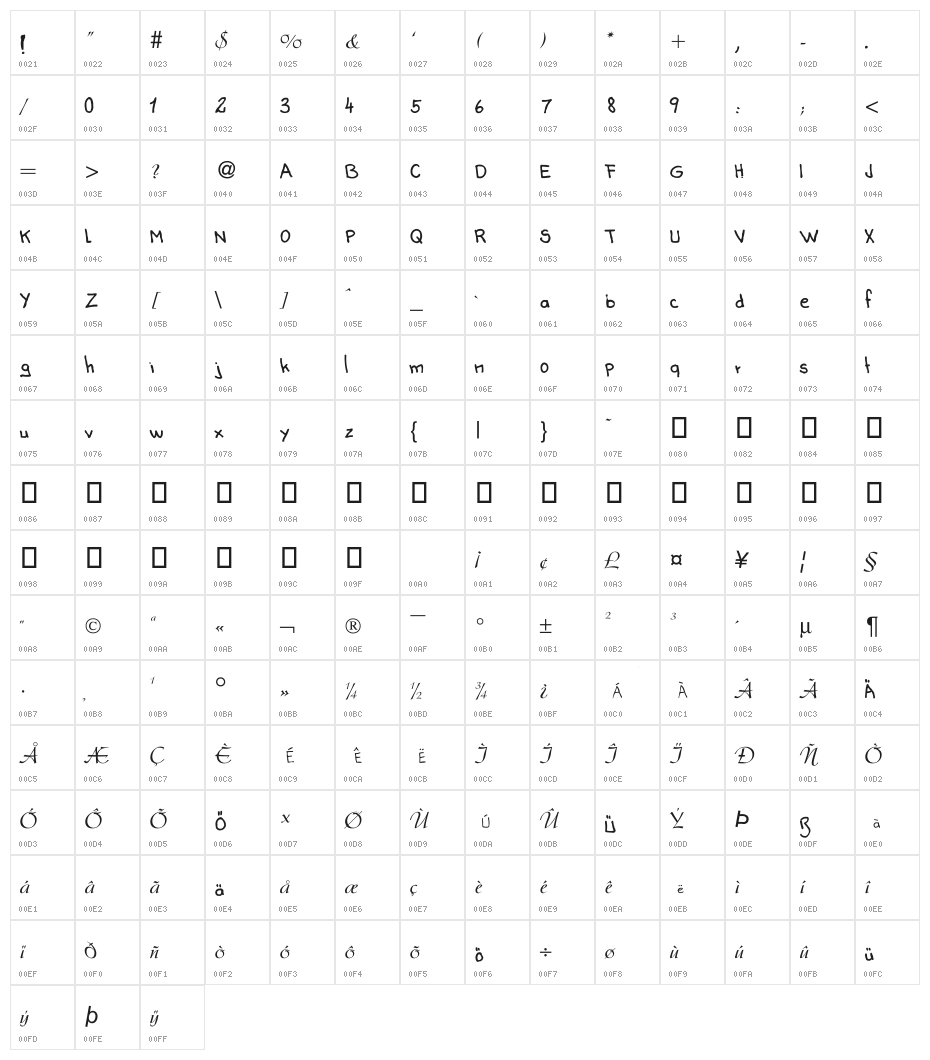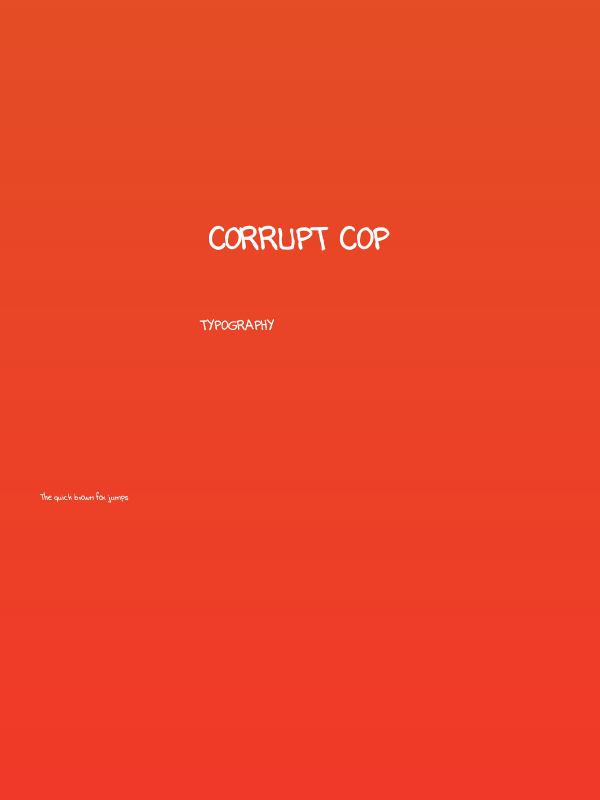
corrupt cop Font
| Stile generale | Casual, Playful |
| Caso d'uso | Headlines, Informal text, Creative projects |
| Progetti proposti | Ideal for children's books, greeting cards, casual branding, and playful social media graphics. |